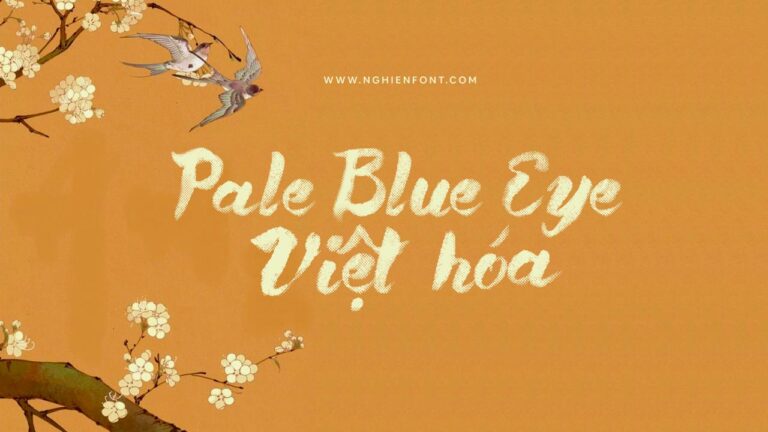
LNTH Pale Blue Eye là font viết tay dạng brush với các nét chữ được thiết kế giống như kiểu chữ thư pháp mang đến một vẻ đẹp hoàn hảo cho các thiết kế dạng retro hoặc cũng có thể sử dụng cho các thiết kế hiện đại. Phông chữ này phù hợp cho các thiết kế như tiêu đề, poster, quotes, bìa truyện, tạp chí…
Font việt hóa LNTH Pale Blue Eye Preview